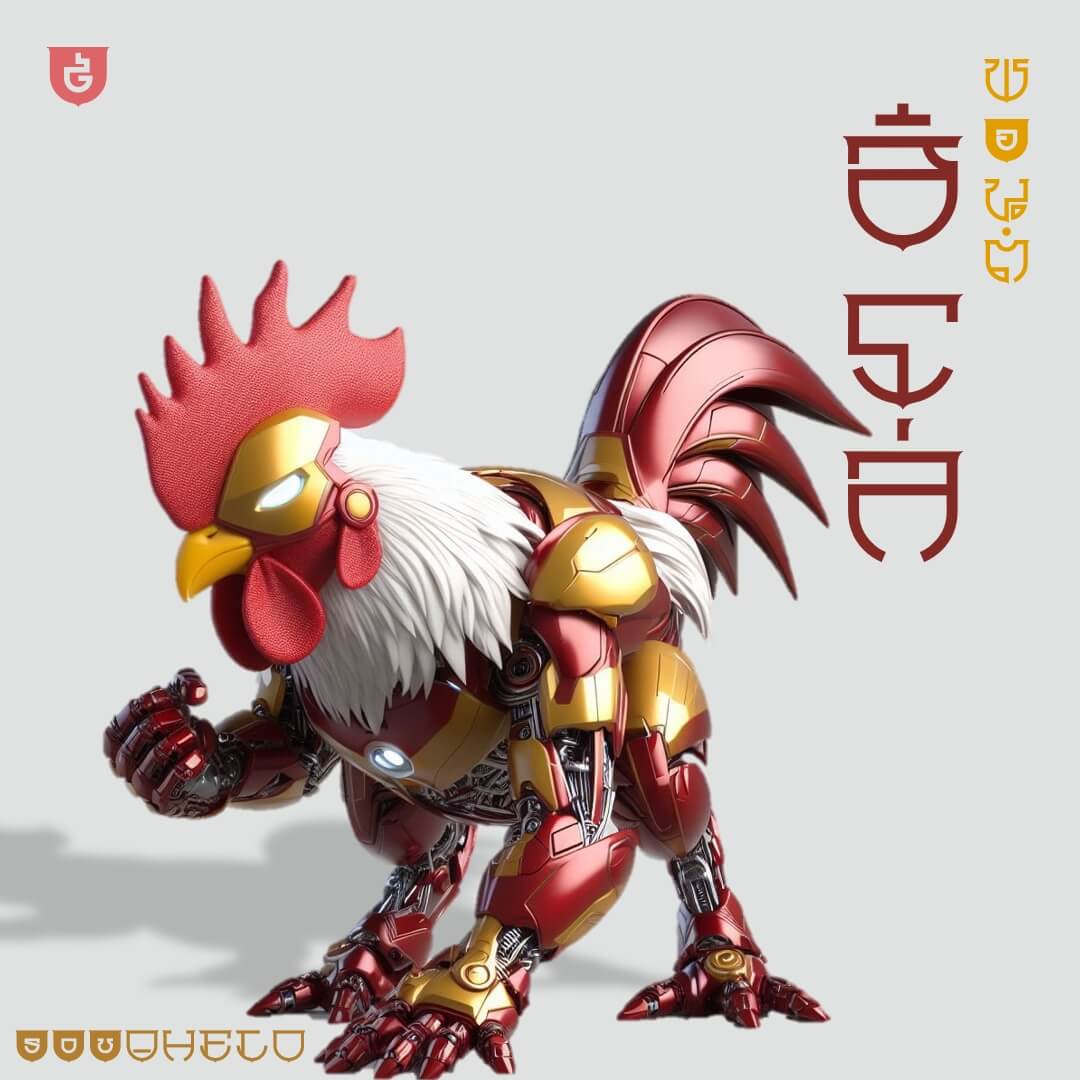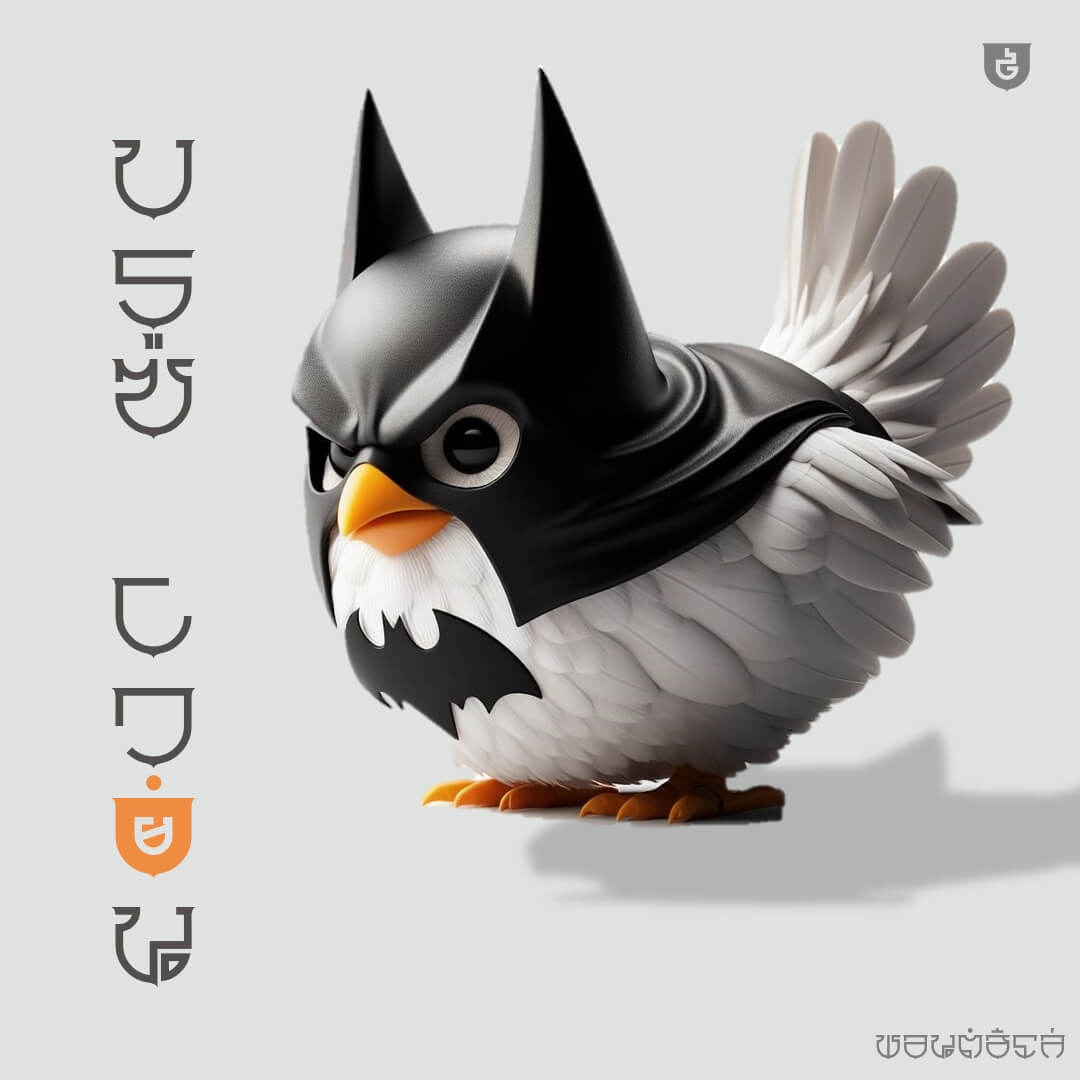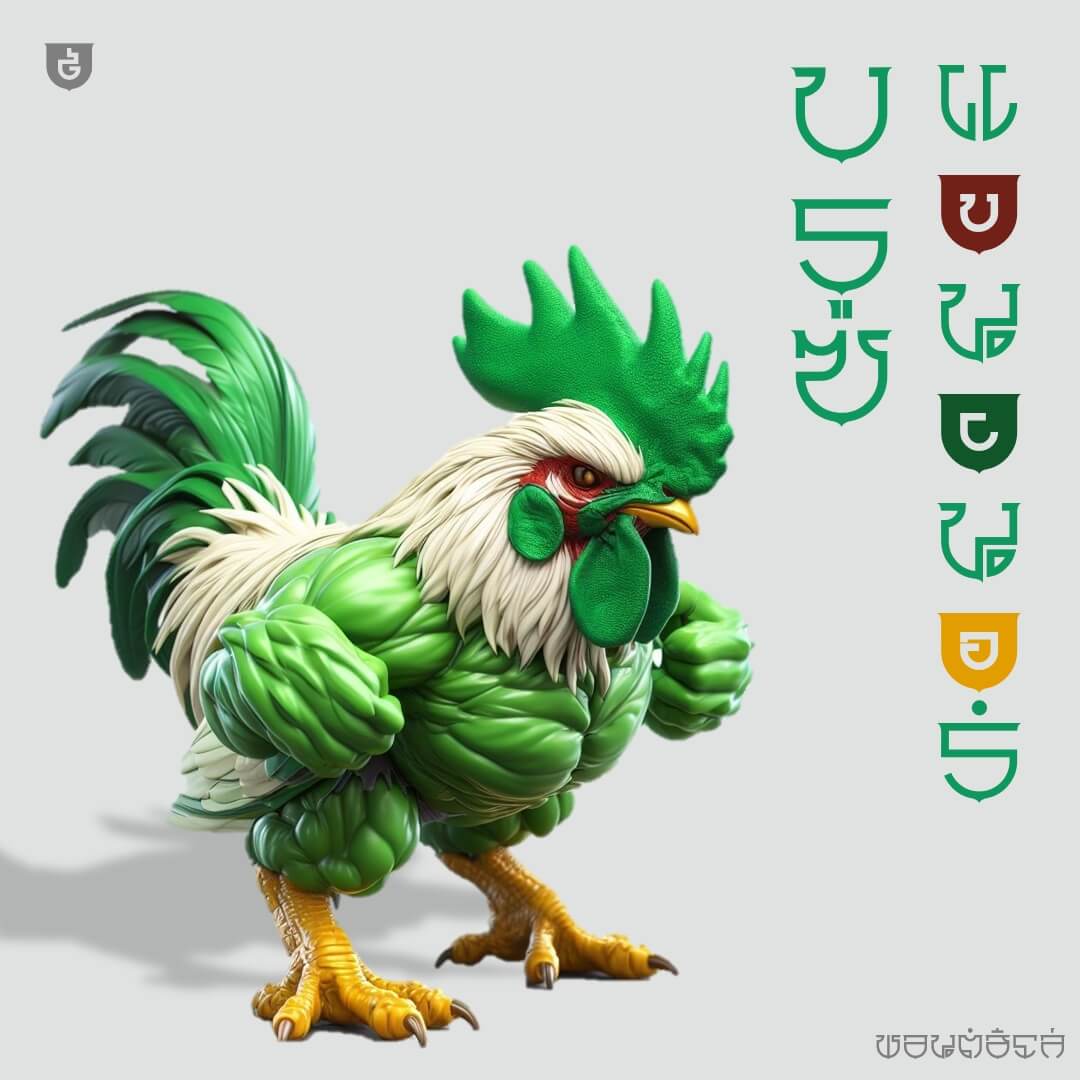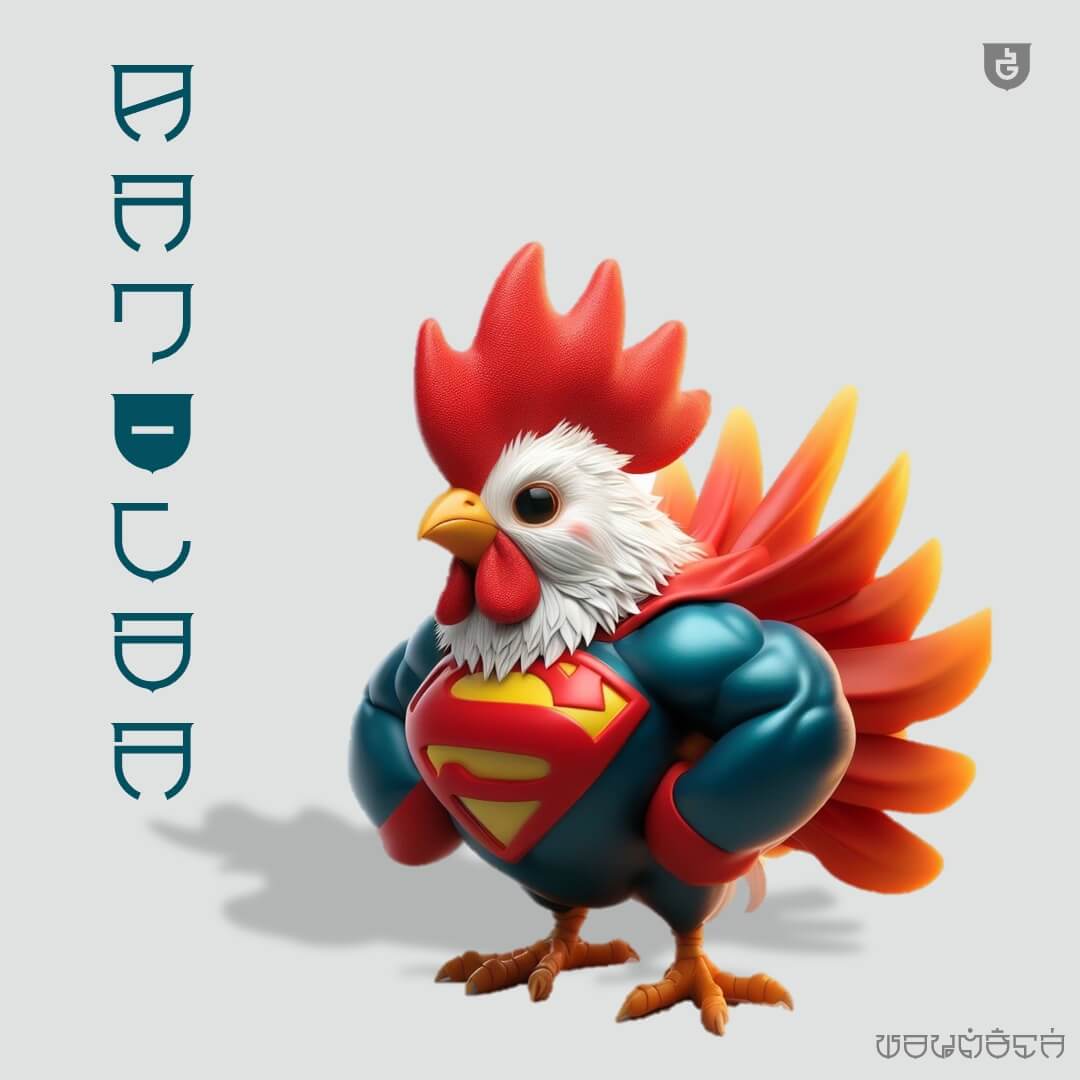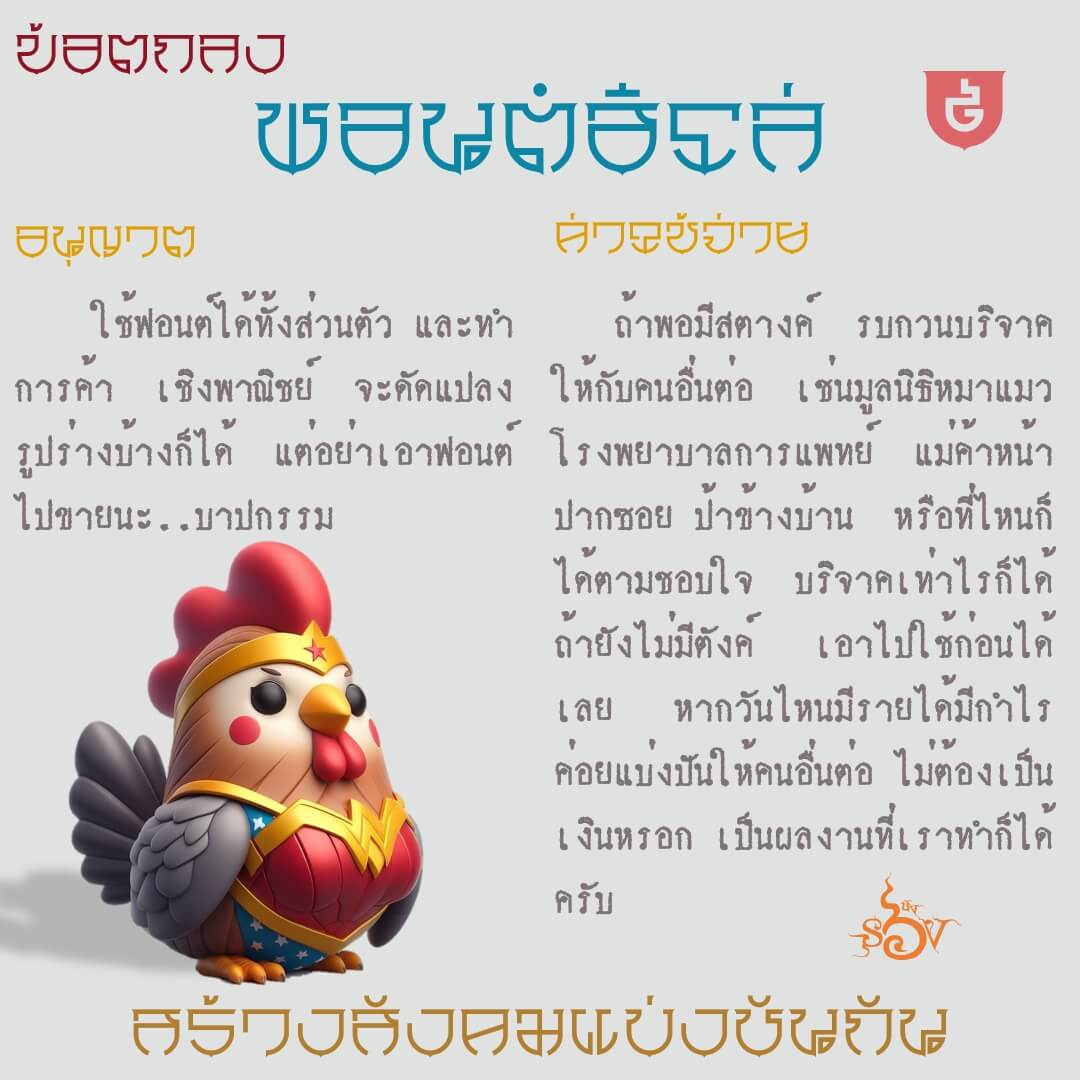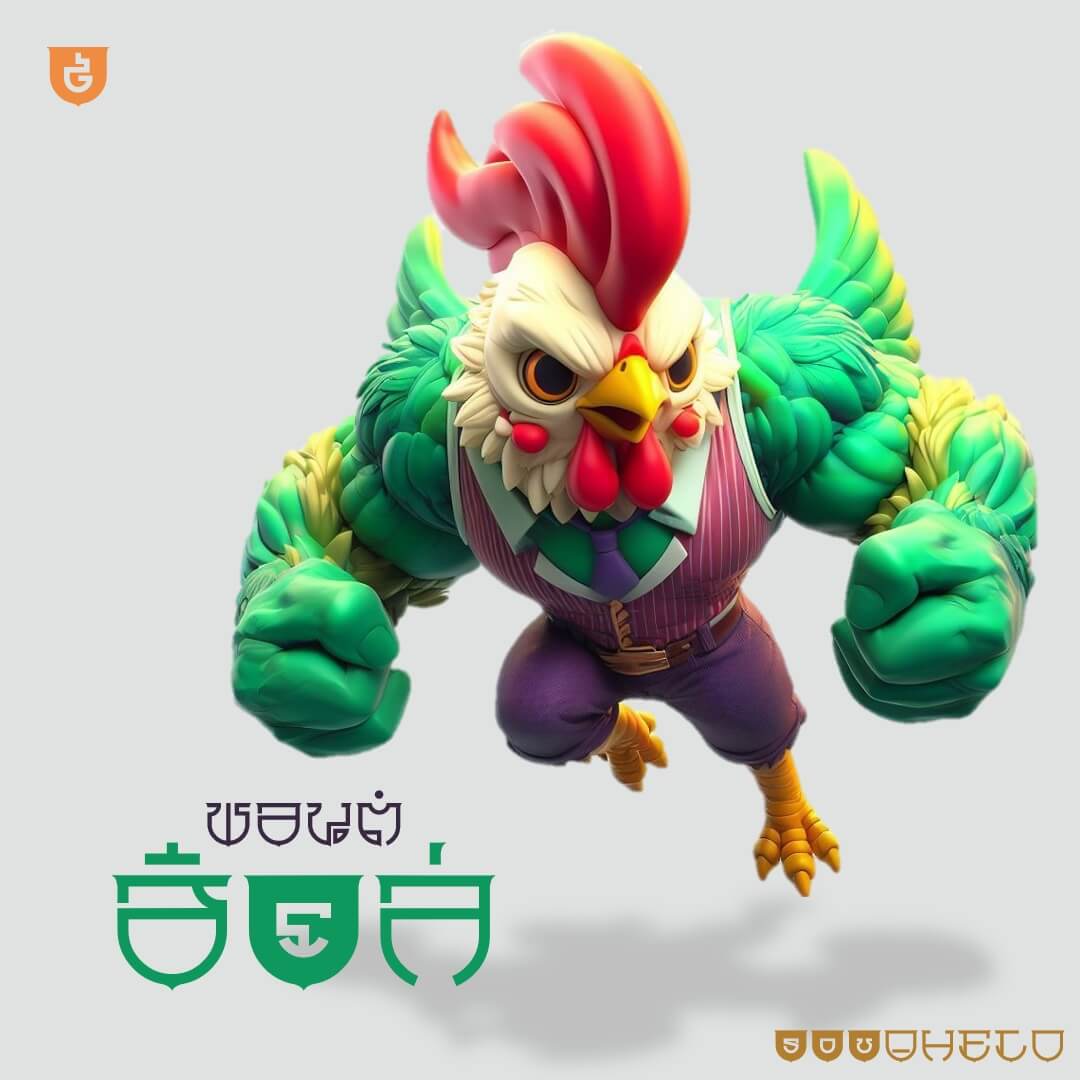
ฮีโล่ (SOV_helo)
ฟอนต์ฮีโล่ – รูปร่างจากรูปโล่ รูปประกอบจากฮีโร่ (ตัวหนังสืออ่านยาก เพราะเป็นโลกคู่ขนาน จักรวาลกุ๊กไก่)
เบื้องหลังการออกแบบ : ฟอนต์ ฮีโล่